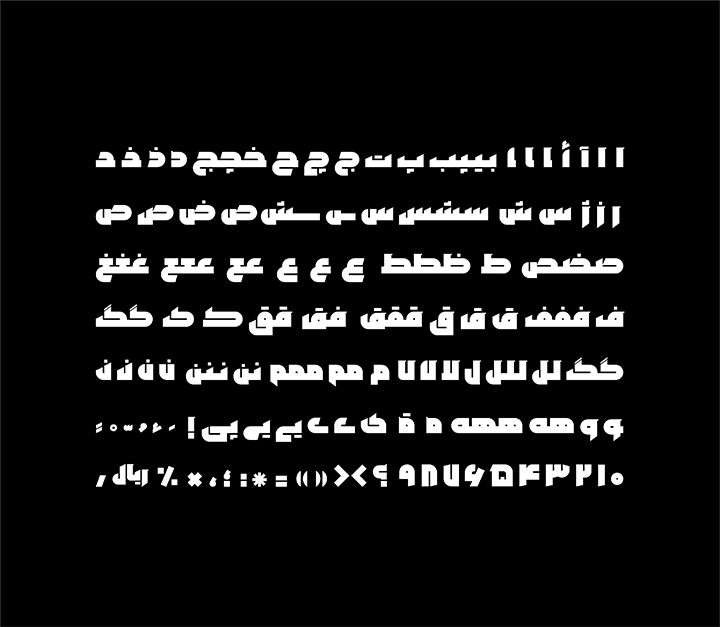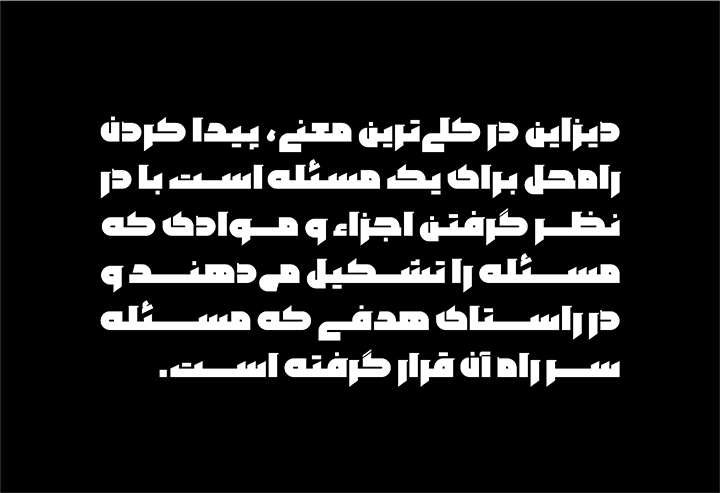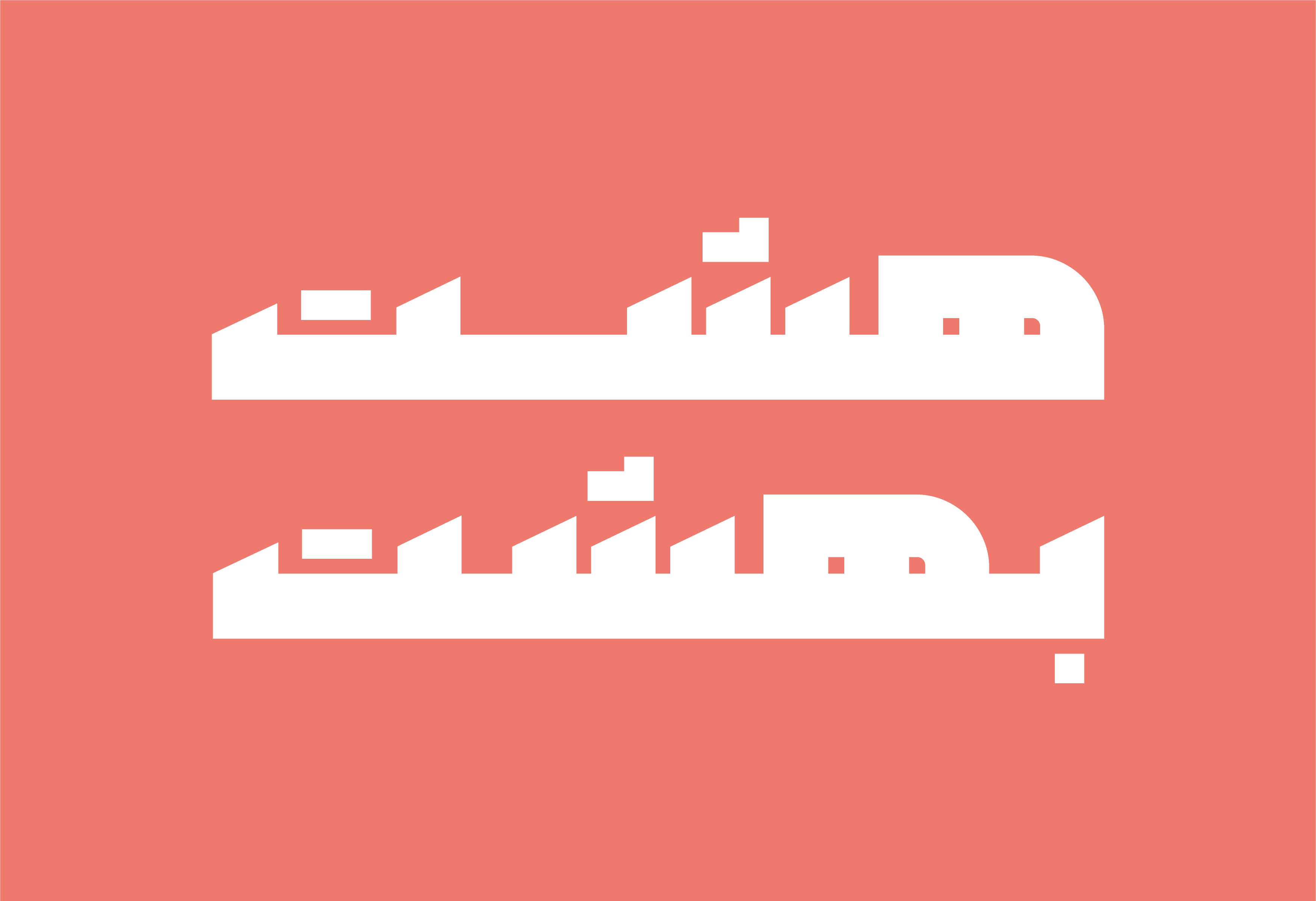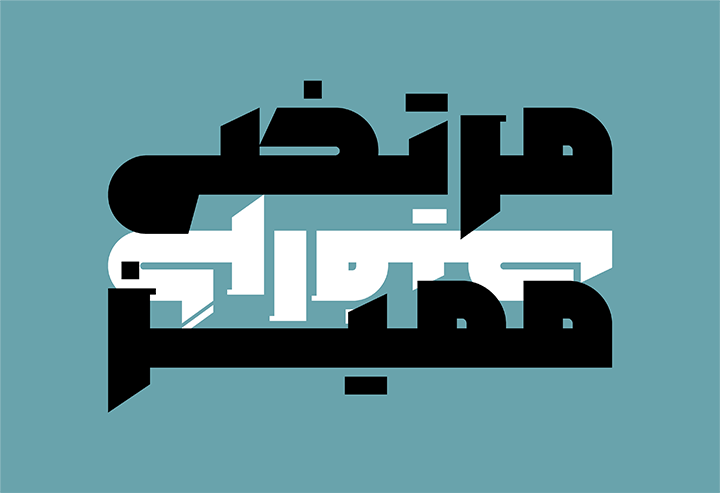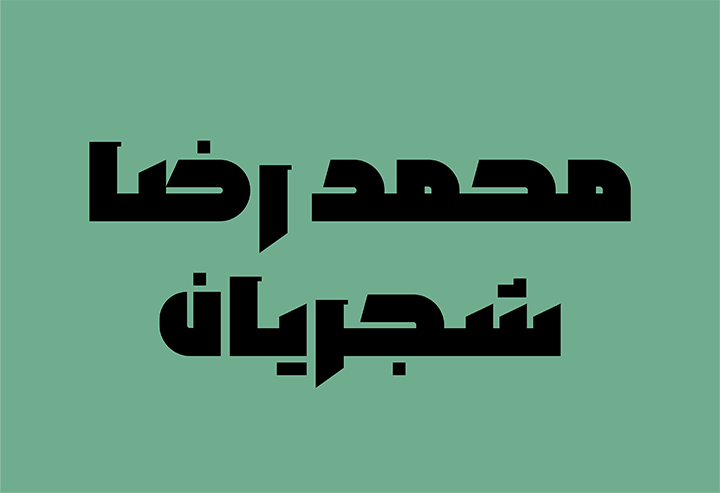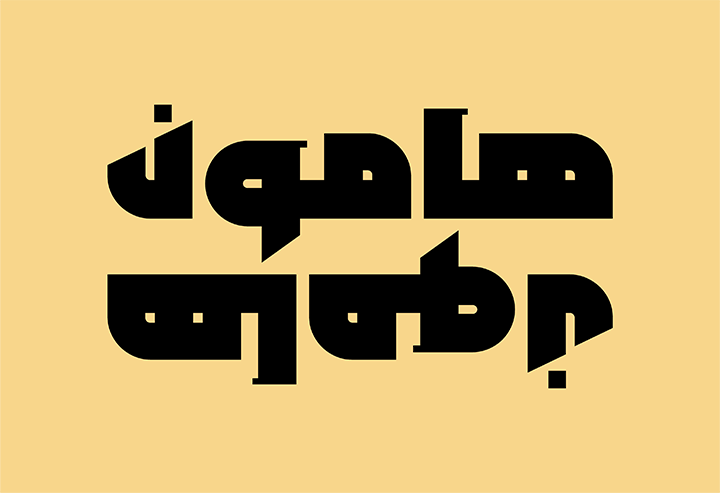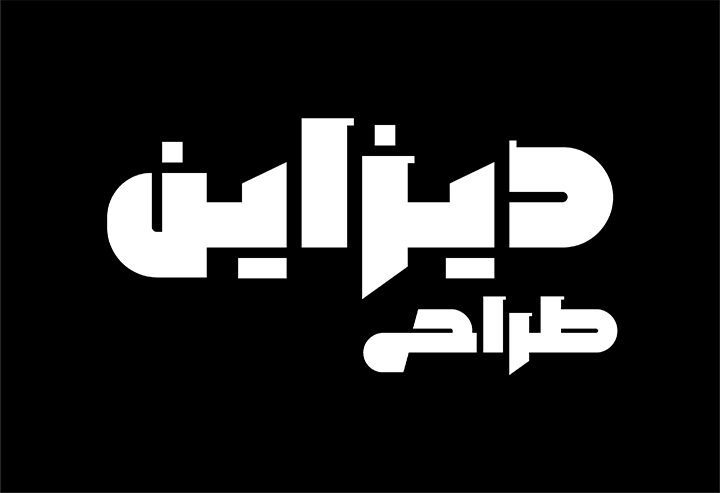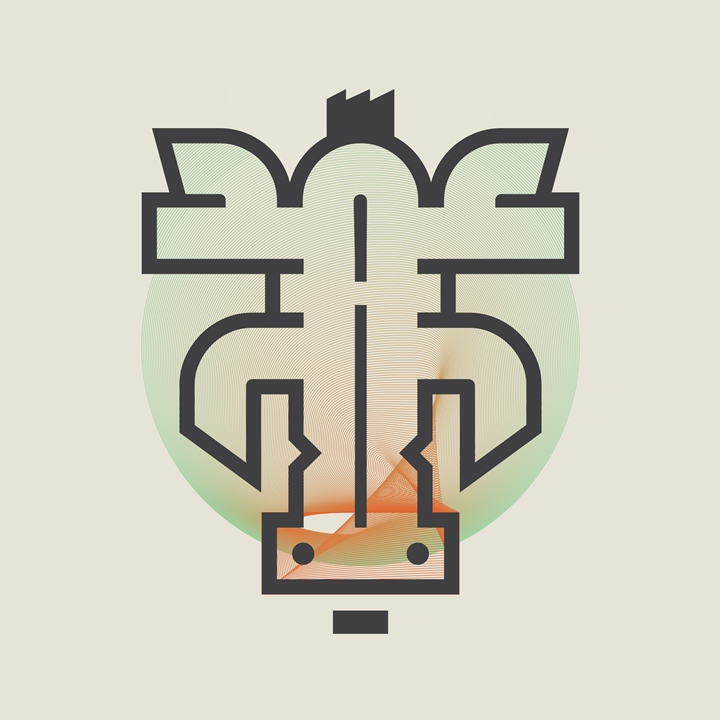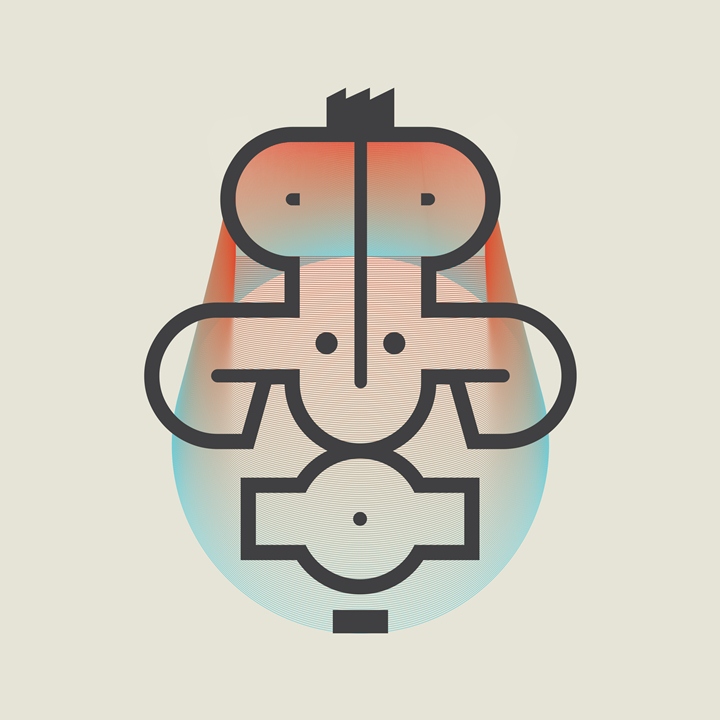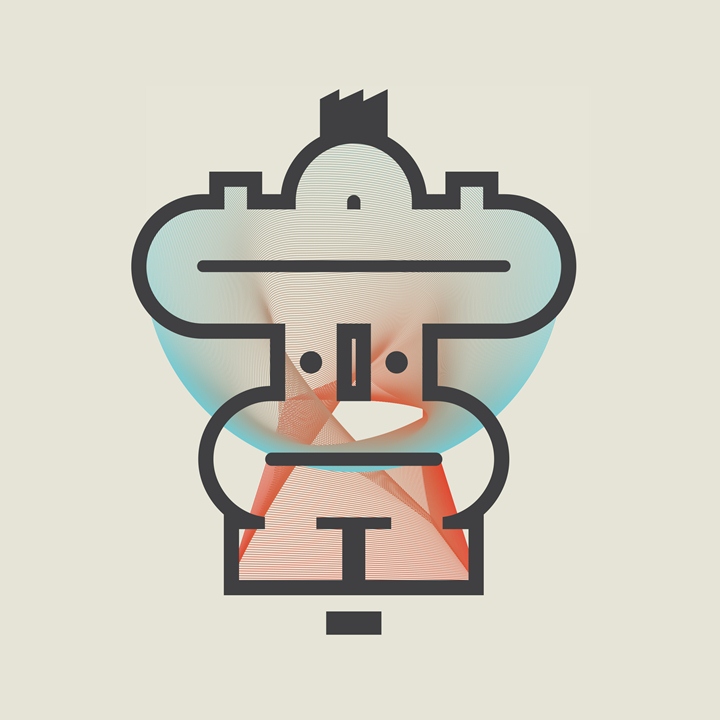
قلم ارشد font Arshad
قلم ارشد
کاری از حامد حکیمی
درباره قلم ارشد
داستان طراحی فونت ارشد از سال ١٣٩٥ به بهانه استفاده در يک فضای گرافيكی كاملا شخصی، برای طراحی پوستر و نشان نوشتاری شروع شد. همين بهانه كافی بود تا خانواده‌ای از حروف ضخيم در كنار هم قرار گيرند و تايپ فيسی به جهت استفاده فرمی در كار ديزاين شكل گيرد. فونت ارشد در استوديو مشق توسط حامد حكيمی با همكاری مسعود جزنی، زهرا ابراهيم‌زاده و مهتاب ذاكری ساخته و طراحی شده است. لطفا در حين استفاده از قلم ارشد با زدن كليدهای Alt+H و Alt+Space از جایگزین‌های فرمی ديگر گليف‌ها استفاده كنيد.